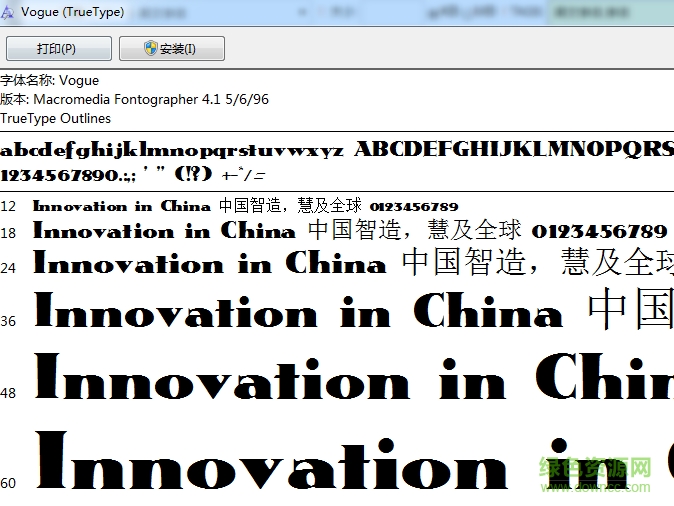
VOGUE字體是一款超好用的英文字體,該字體是用于VOGUE雜志上的一款個性字體,該字體刊登在時尚雜志上能夠凸顯時尚魅力,字體適用于各大雜志、平面設(shè)計、ppt領(lǐng)域,有需要的朋友就來綠色資源網(wǎng)下載使用吧!
VOGUE字體是一款英文字體,該字體獨有的線條,讓用戶能夠輕松記住它,有需要的朋友就趕快來綠色資源網(wǎng)下載吧!